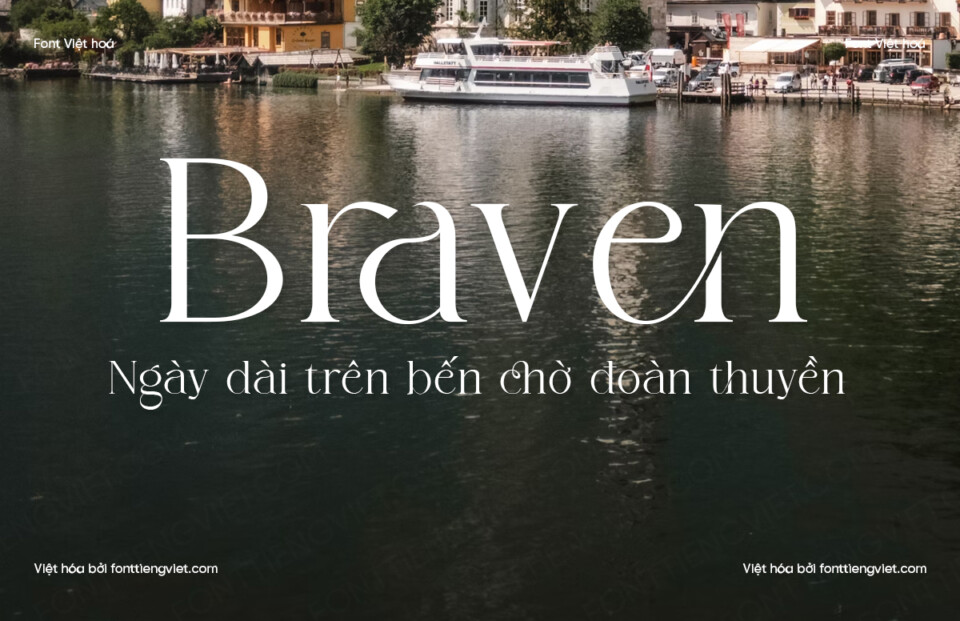
Font Việt hóa 1FTV VIP Braven Regular
Bộ Font Việt hóa 1FTV VIP Braven Regular Tuyệt Đẹp Dành Cho Thiết Kế Đồ Họa
Giới thiệu về Font Việt hóa 1FTV VIP Braven Regular
Trong thế giới thiết kế đồ họa hiện đại, việc tìm kiếm một bộ font vừa mang tính nghệ thuật vừa hỗ trợ tốt tiếng Việt là điều vô cùng quan trọng. Font Việt hóa 1FTV VIP Braven Regular nổi lên như một lựa chọn hàng đầu cho các nhà thiết kế chuyên nghiệp lẫn nghiệp dư. Đây là một phông chữ thuộc phong cách Serif cổ điển nhưng lại mang hơi thở hiện đại với các đường nét tinh xảo và sắc nét. Khi sử dụng Font Miễn Phí này, bạn sẽ nhận thấy sự chỉn chu trong từng ký tự, từ khoảng cách cho đến độ dày của nét chữ đều được tính toán kỹ lưỡng. Bộ font này đặc biệt phù hợp cho các dự án yêu cầu sự sang trọng và đẳng cấp, giúp nâng tầm giá trị hình ảnh cho mọi tác phẩm sáng tạo của người dùng Việt.
Đặc điểm nổi bật của Font Việt hóa 1FTV VIP Braven Regular
Thiết kế tinh tế và chuyên nghiệp
Lý do khiến Font Việt hóa 1FTV VIP Braven Regular được yêu thích chính là cấu trúc chữ rất cân đối. Các chân chữ (serif) được thiết kế vuông vắn, tạo cảm giác vững chãi và đáng tin cậy. Dòng VIP Braven này không chỉ dừng lại ở việc hiển thị văn bản thông thường mà còn là một công cụ truyền tải cảm xúc mạnh mẽ. Các nhà thiết kế thường sử dụng nó cho các tiêu đề sách, tạp chí thời trang hoặc các bộ nhận diện thương hiệu cao cấp. Khả năng hiển thị tốt trên cả màn hình kỹ thuật số và bản in giúp bộ font này trở nên đa dụng trong mọi hoàn cảnh thiết kế khác nhau.
Khả năng tương thích và tối ưu hóa tiếng Việt
Một trong những rào cản lớn nhất khi sử dụng font ngoại quốc là lỗi dấu tiếng Việt. Tuy nhiên, với phiên bản Font Việt hóa 1FTV VIP Braven Regular, mọi ký tự đặc biệt như “ă”, “â”, “đ” hay các dấu thanh đều được xử lý mượt mà. Đội ngũ việt hóa đã tinh chỉnh để các dấu không bị quá cao hay quá dính vào thân chữ, đảm bảo tính thẩm mỹ cao nhất. Điều này giúp các bạn học sinh, sinh viên hay giáo viên có thể dễ dàng ứng dụng vào việc làm bài thuyết trình, thiết kế báo tường hoặc tài liệu giảng dạy mà không lo ngại về vấn đề hiển thị hay lỗi font gây khó chịu cho người xem.
Ứng dụng thực tế của Font Việt hóa 1FTV VIP Braven Regular
Thiết kế in ấn và quảng cáo
Đối với mảng in ấn, Font Việt hóa 1FTV VIP Braven Regular tỏa sáng trong các mẫu danh thiếp, thiệp mời đám cưới hay các poster sự kiện trang trọng. Nhờ độ tương phản giữa các nét thanh và nét đậm, phông chữ này giúp thu hút ánh nhìn ngay từ giây phút đầu tiên. Bạn có thể kết hợp nó với các font chữ không chân (sans-serif) để tạo nên một bố cục hài hòa và chuyên nghiệp. Trong giáo dục, bộ font này cũng thường được dùng để thiết kế chứng chỉ hoặc bằng khen, mang lại vẻ ngoài trang trọng và đầy tự hào cho người nhận.
Sáng tạo nội dung trên mạng xã hội
Trong kỷ nguyên số, việc tạo ra các hình ảnh quote hay banner trên Facebook, Instagram đòi hỏi sự khác biệt. Sử dụng Font Việt hóa 1FTV VIP Braven Regular sẽ giúp bài đăng của bạn trông nghệ thuật hơn hẳn các font mặc định nhàm chán. Đây là cách đơn giản nhất để gây ấn tượng với khán giả và xây dựng phong cách cá nhân độc đáo. Hãy thử nghiệm với các màu sắc tương phản như chữ trắng trên nền tối để thấy rõ sự sắc sảo mà bộ font này mang lại cho nội dung của bạn.
Kết luận về bộ Font Việt hóa 1FTV VIP Braven Regular
Tổng kết lại, đây là một bộ tài nguyên vô giá cho bất kỳ ai đang làm việc trong lĩnh vực sáng tạo. Với sự kết hợp hoàn hảo giữa thẩm mỹ và công năng, Font Việt hóa 1FTV VIP Braven Regular xứng đáng có một vị trí trong bộ sưu tập của bạn. Việc sở hữu một phông chữ chất lượng không chỉ giúp tiết kiệm thời gian chỉnh sửa mà còn khẳng định sự chuyên nghiệp trong công việc. Nếu bạn đang tìm kiếm giải pháp tối ưu cho dự án sắp tới, đừng quên tải ngay Font Miễn Phí, Font Việt Hóa, Font Việt hóa 1FTV VIP Braven Regular để trải nghiệm sự khác biệt. Hãy để những nét chữ tinh tế này chắp cánh cho những ý tưởng bay xa và tạo nên những sản phẩm truyền thông thực sự ấn tượng và có sức hút lâu bền.